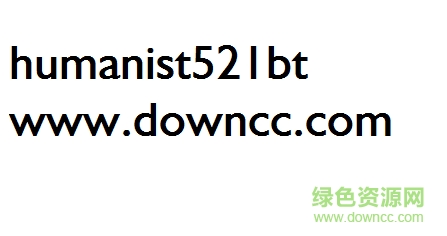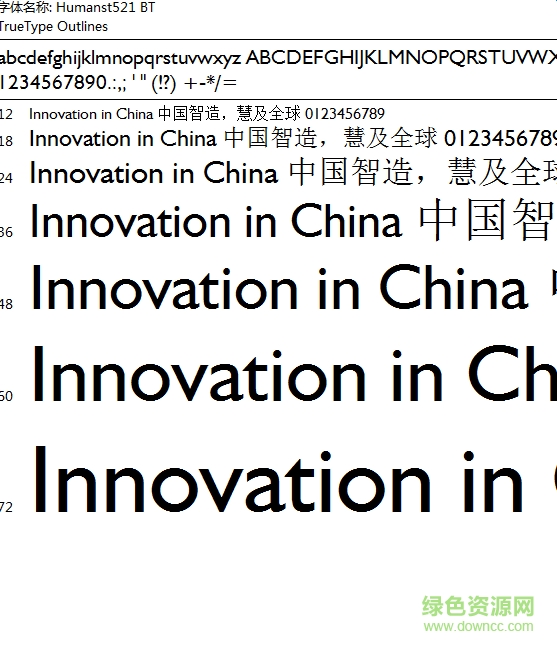
humanist521bt
humanist521bt字體是一款好看的英文字體軟件,該字體非常正式,筆畫一絲不茍,用于英文內(nèi)容設(shè)計排版再合適不過了,有需要就來綠色資源網(wǎng)下載使用吧!
字體介紹
humanist521bt是一款簡單、大方的英文廣告字體,humanist521bt字體筆畫均衡,折角處圓潤沒有棱角。如果你想將其用于商業(yè)用途,則需要聯(lián)系作者取得授權(quán)。
humanist521bt字體
筆畫適中,筆畫流暢,點畫呼應(yīng),造型秀美適意,用在很小的字號時仍具有清晰、明快的閱讀效果!